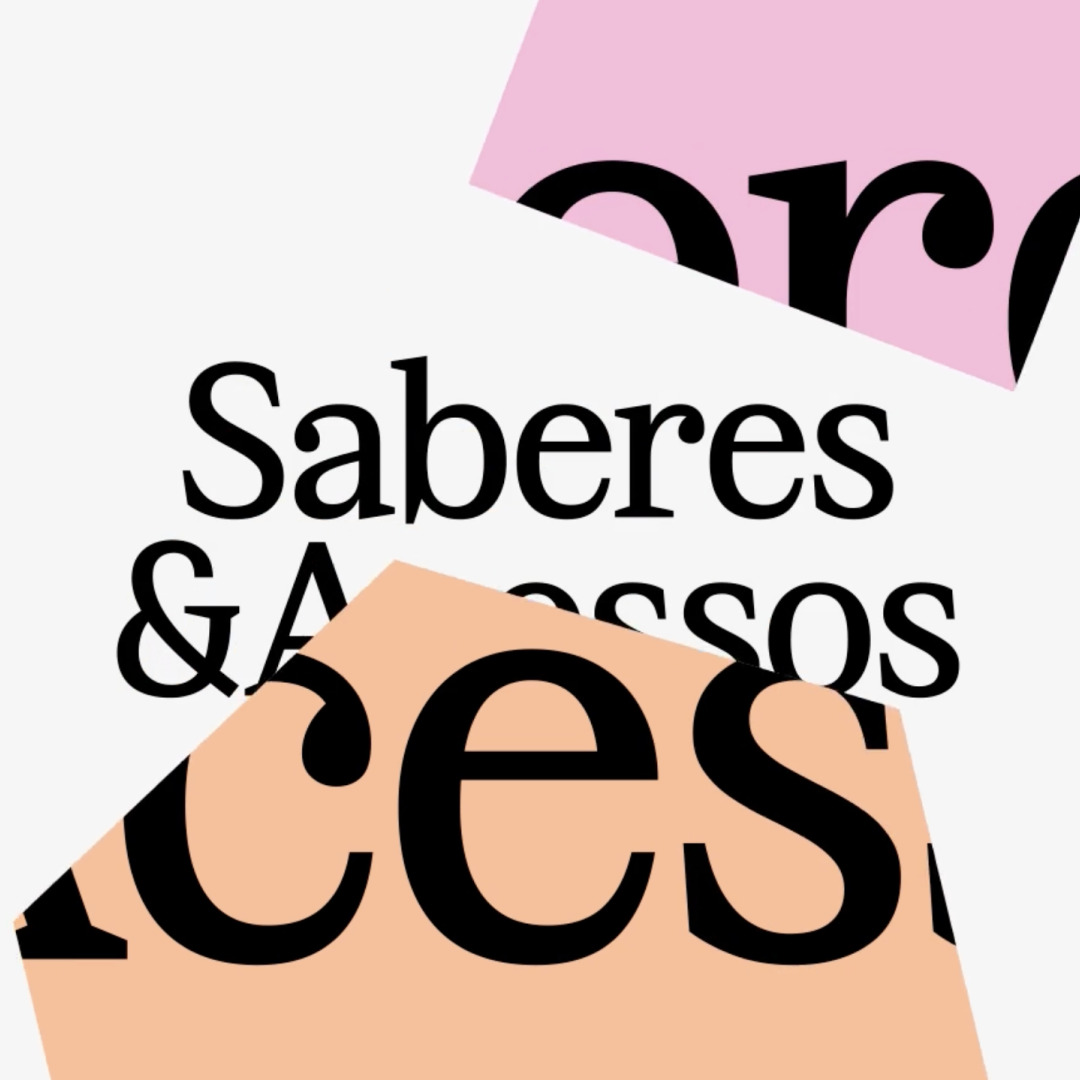
Saberes e Acessos (Знания и доступ) — инклюзивный фестиваль, который прошёл в октябре 2024 в Сан-Карлусе. Фестиваль с лекциями, перформансами и спектаклями организовала инициатива Sesc, которая борется с эйблизмом в Бразилии. За типографику в айдентике Saberes e Acessos отвечает Maregraphe студии CSTM Fonts. Айдентику сделали в студии Papanapa.
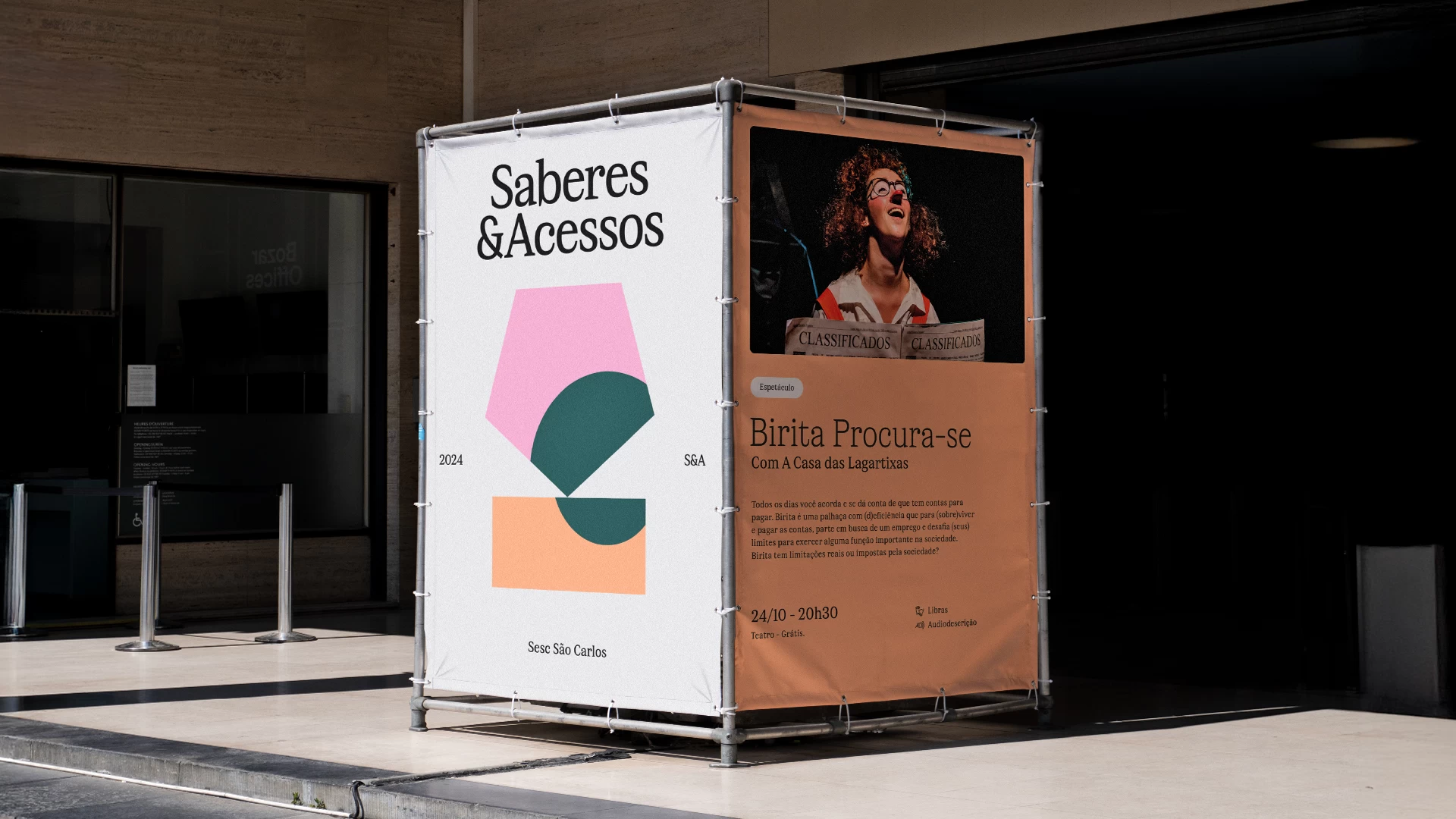
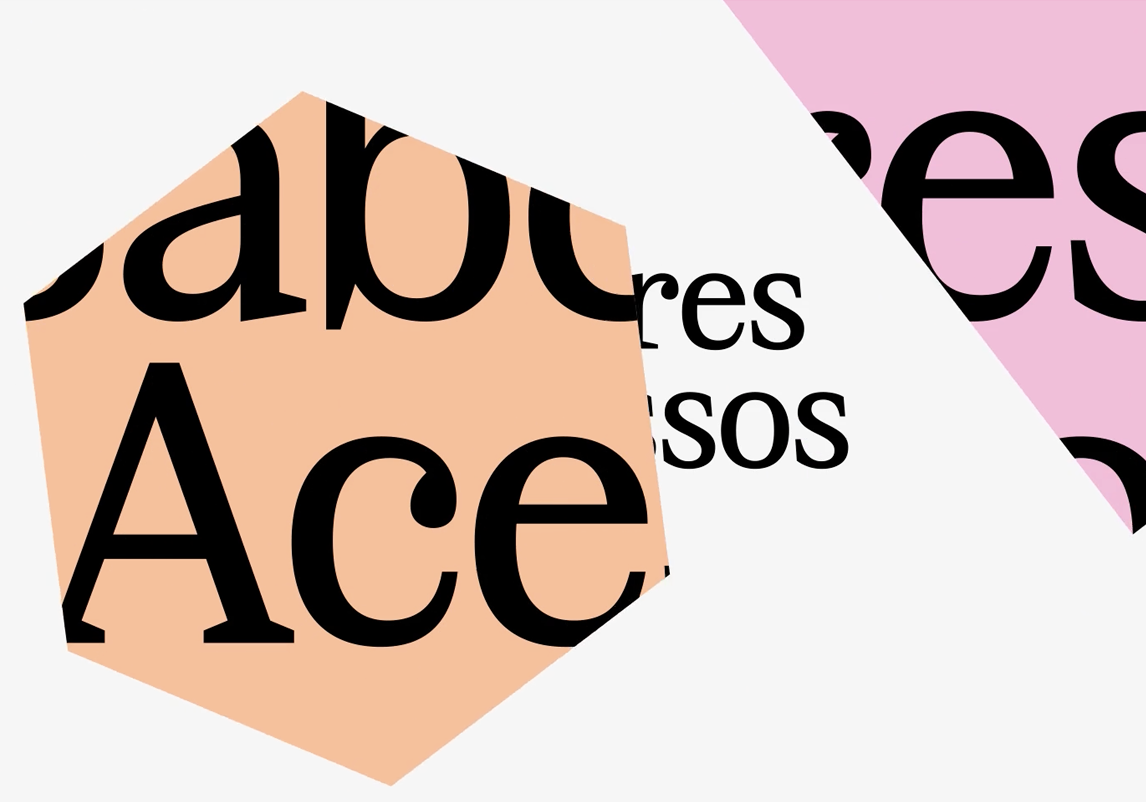
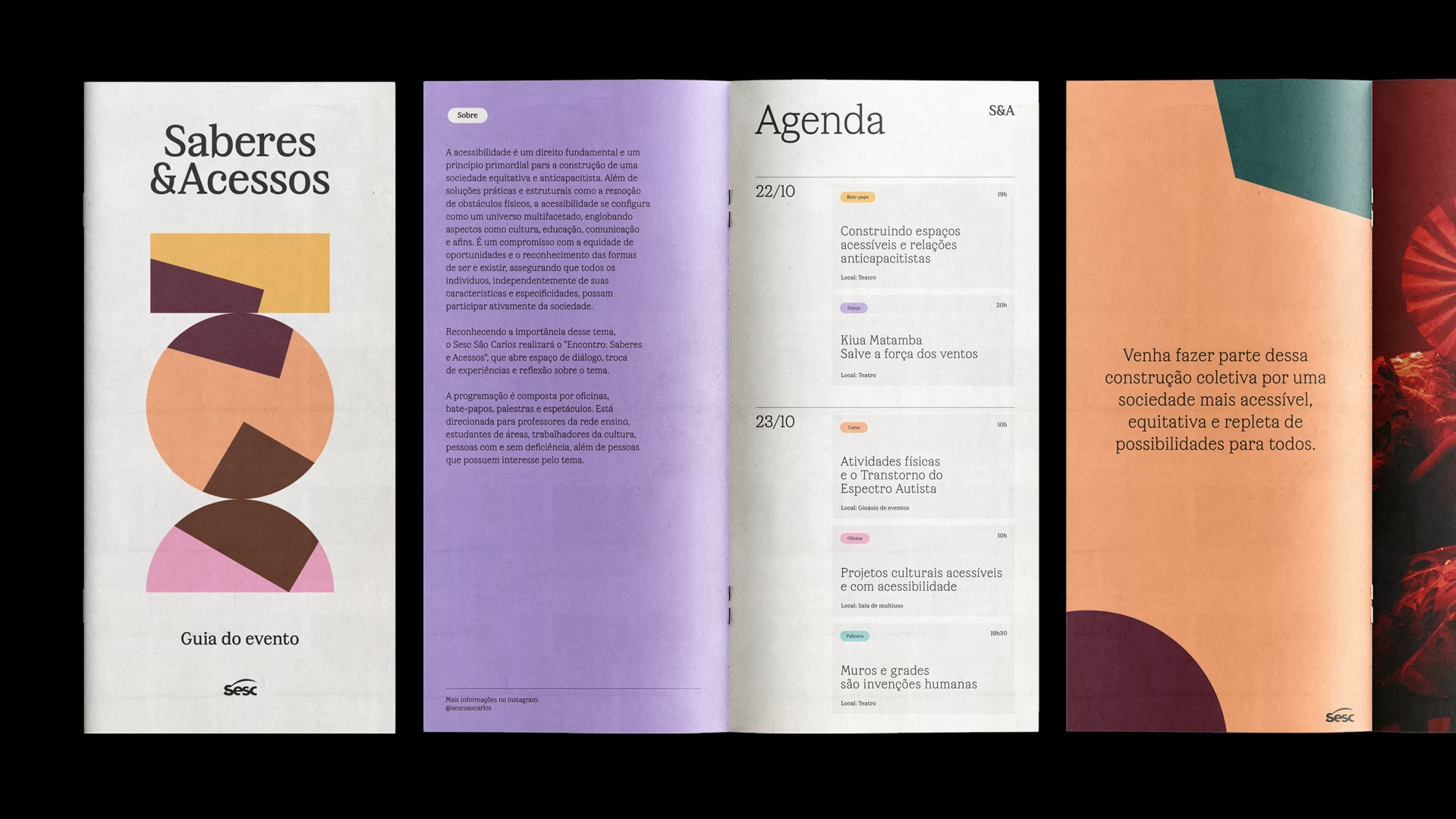
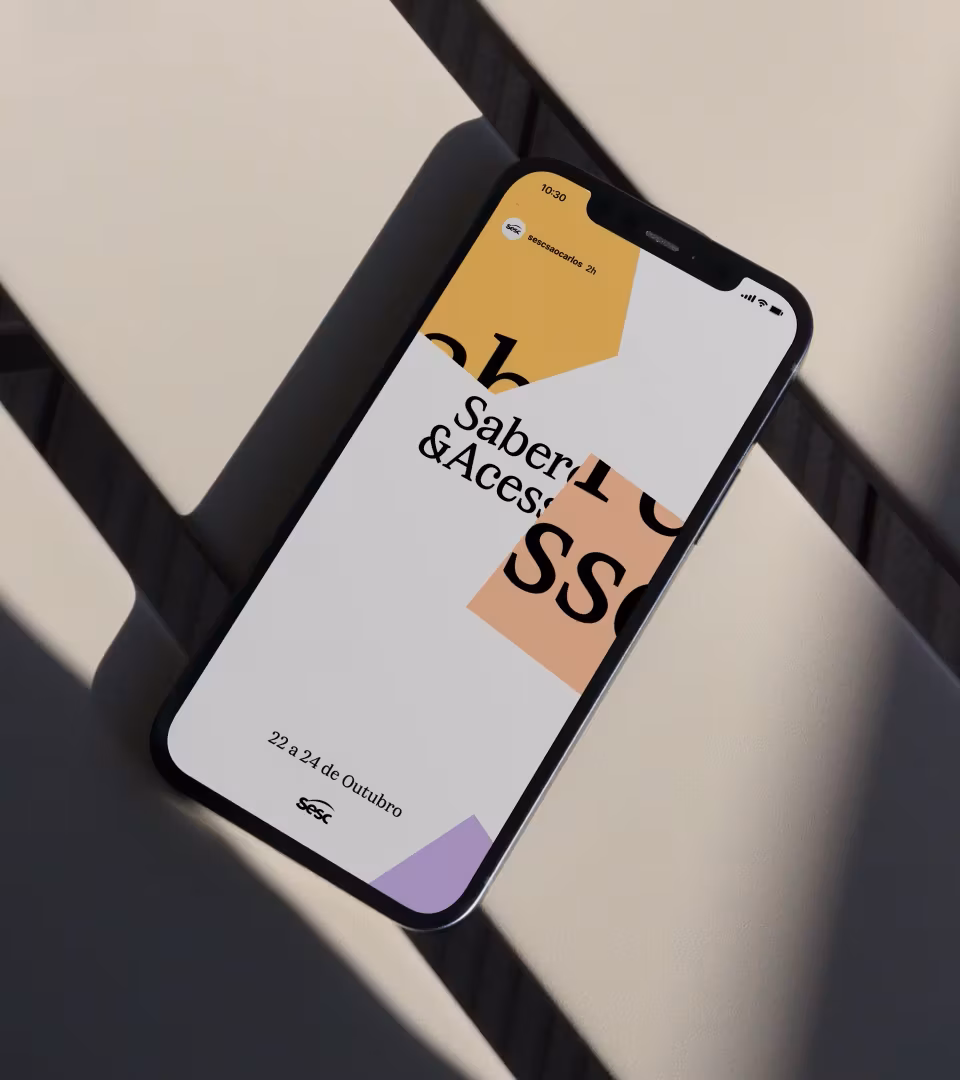
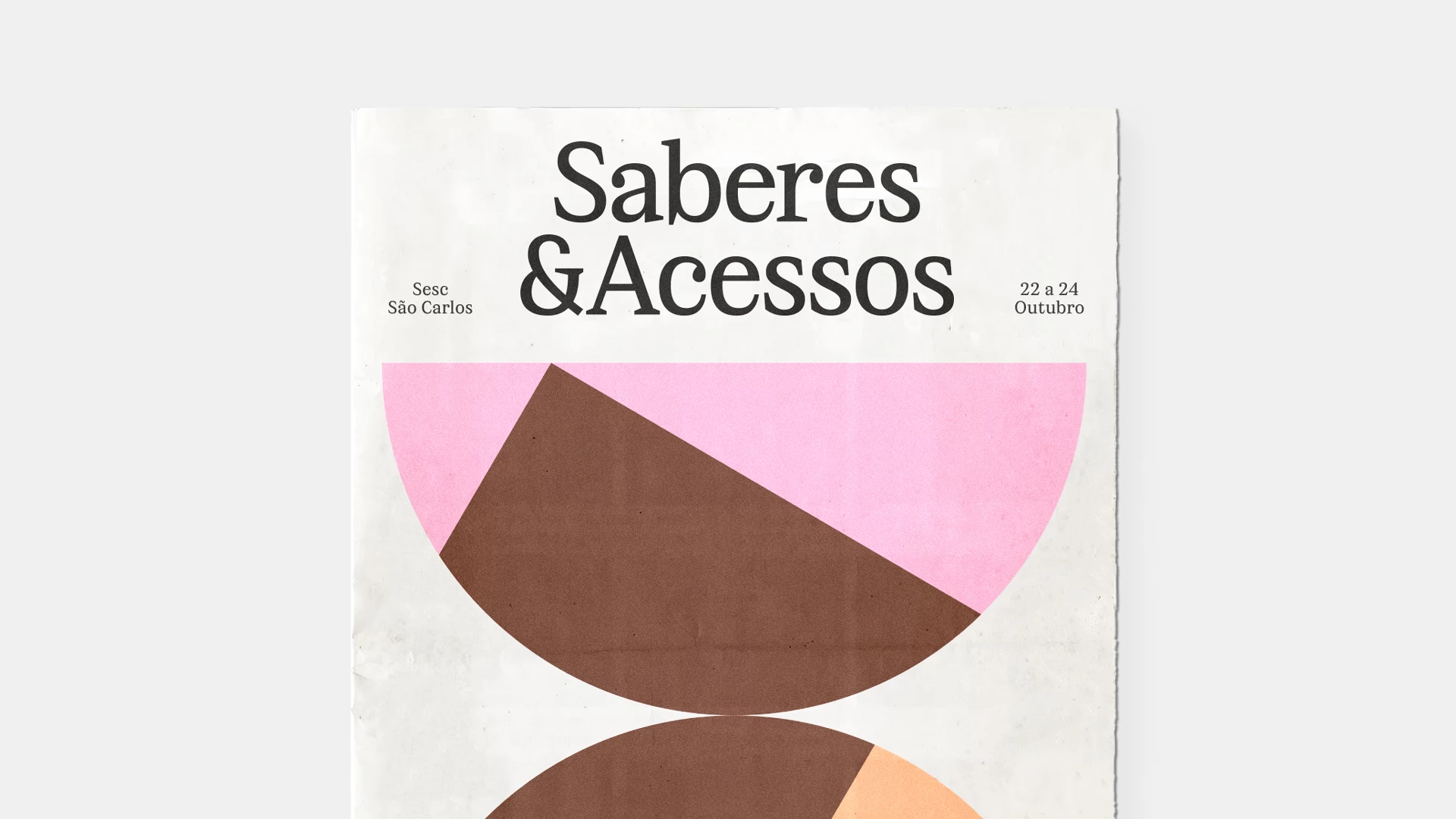
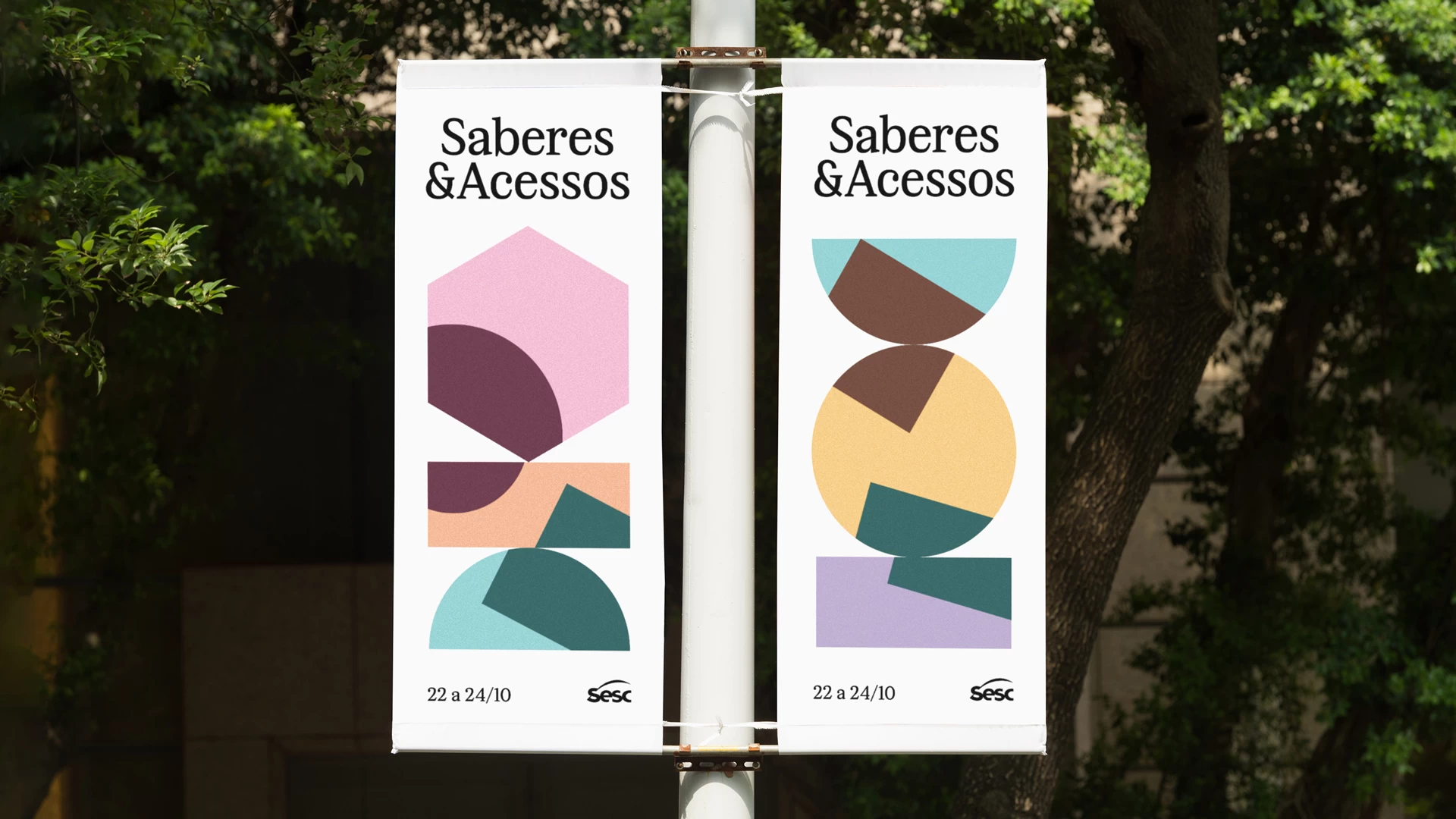
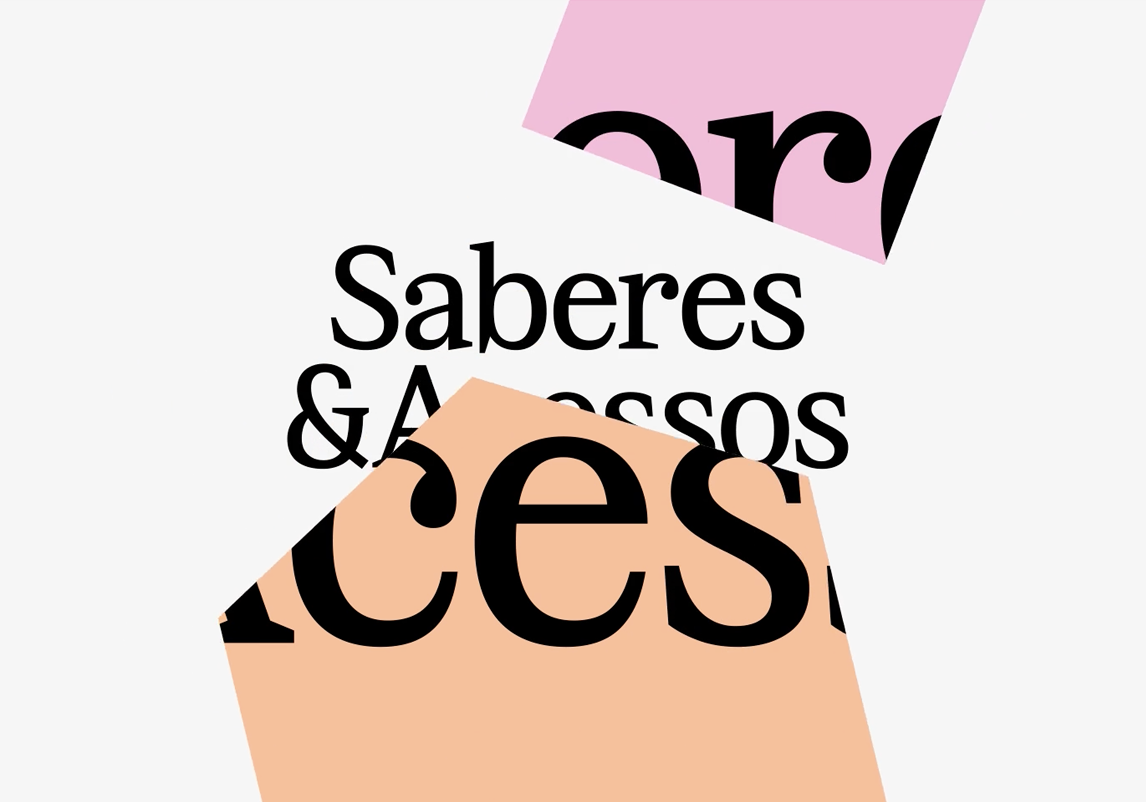
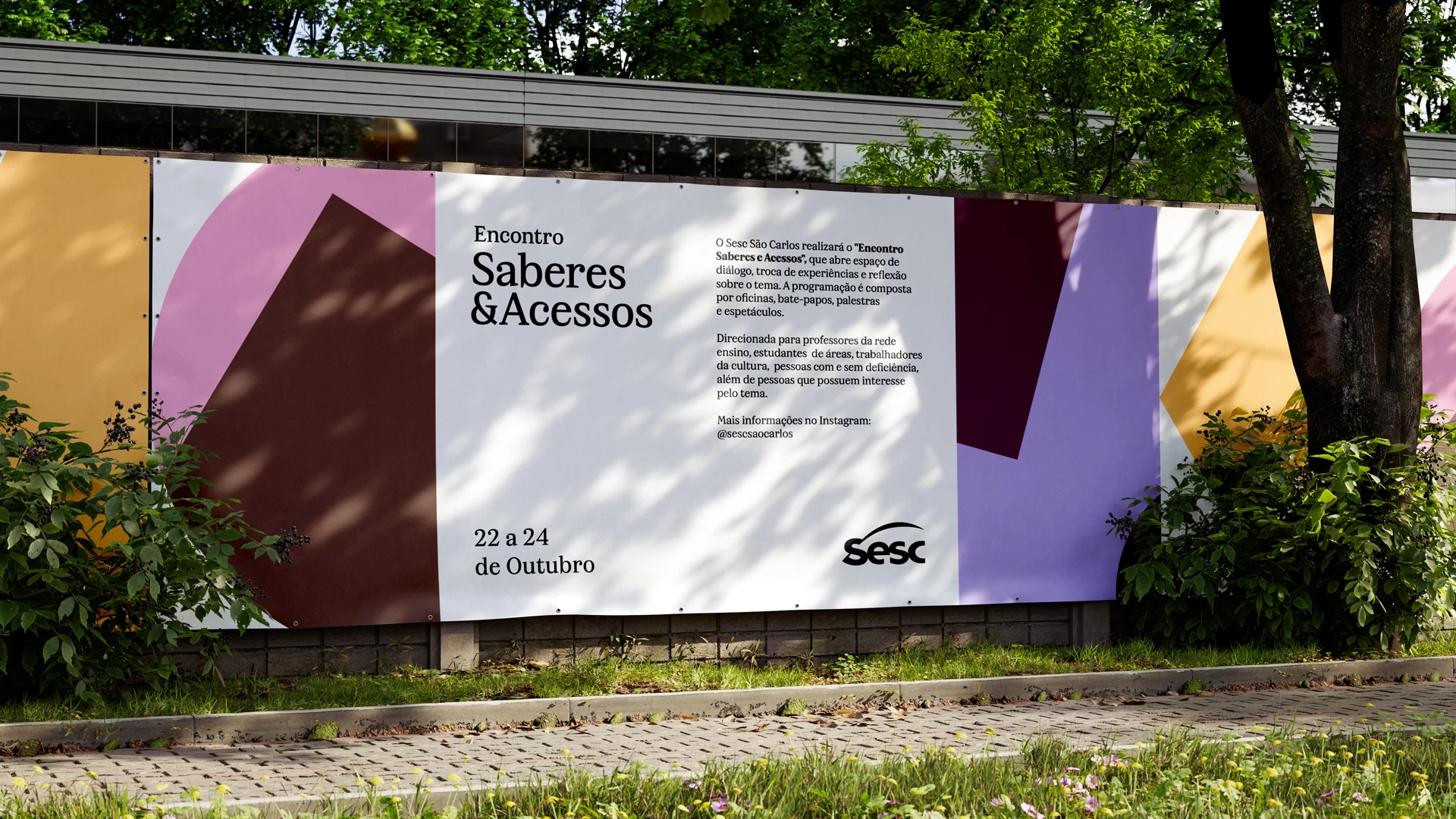
Maregraphe — резкая и компактная современная антиква, вдохновлённая надписью на стене Марсельского мареографа, сделанной в начале XIX века, и французским леттерингом разных времён. В коллекции четыре шрифта — заголовочный Maregraphe Display, текстовый Maregraphe Text, и два безумных шрифта: экстремально узкий Maregraphe Mega Compressed и экстремально широкий Maregraphe Mega Extended.